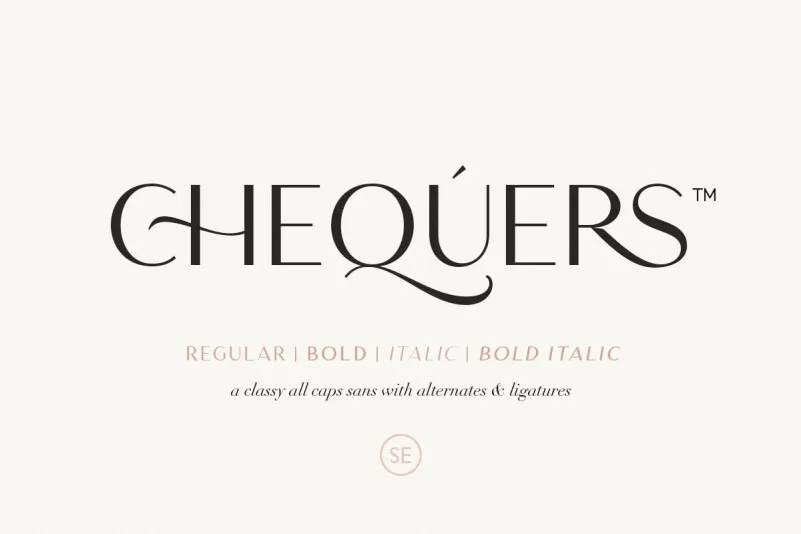
Chequers Font – Fonte Grátis
Chequers Font
A fonte ‘Chequers Font’ é uma elegante tipografia serifada criada por Sarid Ezra, oferecendo uma variedade rica de características e ligaturas que tornam seu projeto ainda mais atraente e distinguido. Este tipo-fonte inclui um conjunto vasto de ligações essenciais que podem ser usadas em apresentações ou logotipos, aumentando consideravelmente o impacto visual dos mesmos. Com quatro estilos distintos para diversas finalidades, a ‘Chequers Font’ é uma opção versátil e prática para designers de todo tipo. A fonte suporta múltiplas línguas e já está PUA (Planejamento Universal de Escrita) codificada, garantindo que qualquer texto em sua base seja renderizado com precisão. A ‘Chequers Font’ é uma escolha ideal para aqueles que buscam um equilíbrio entre elegância e praticidade, oferecendo soluções gráficas perfeitas para trabalhos profissionais ou projetos de design pessoal.